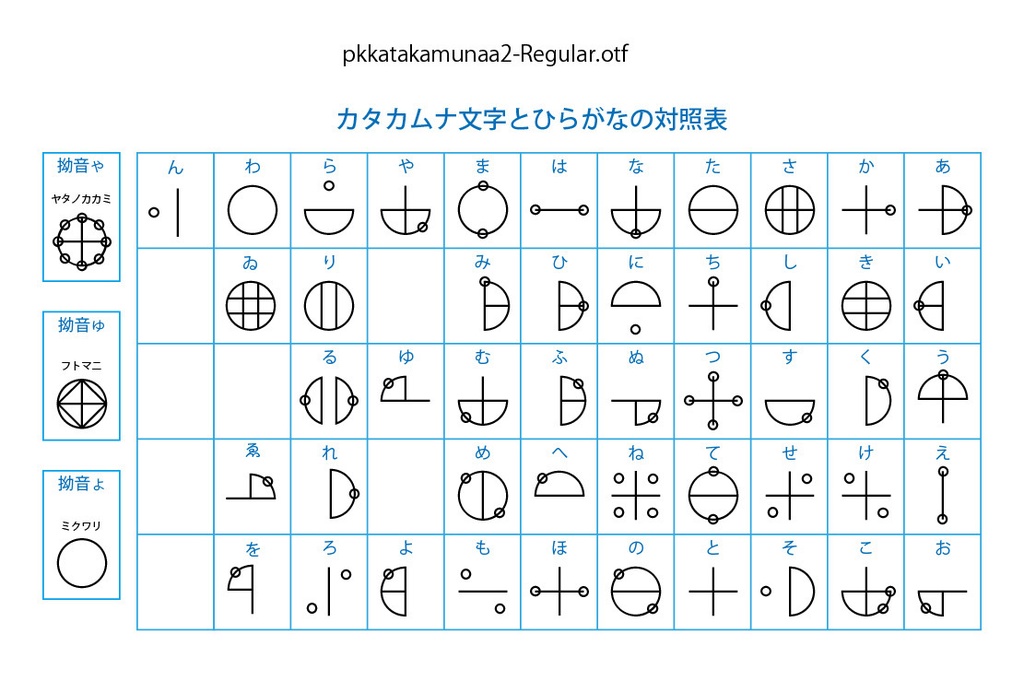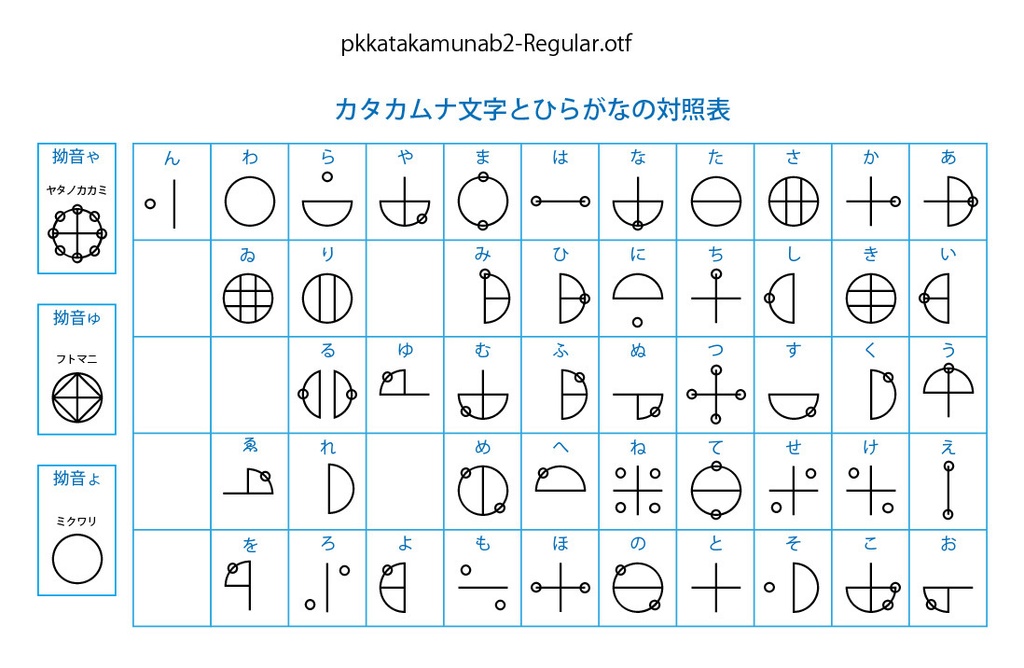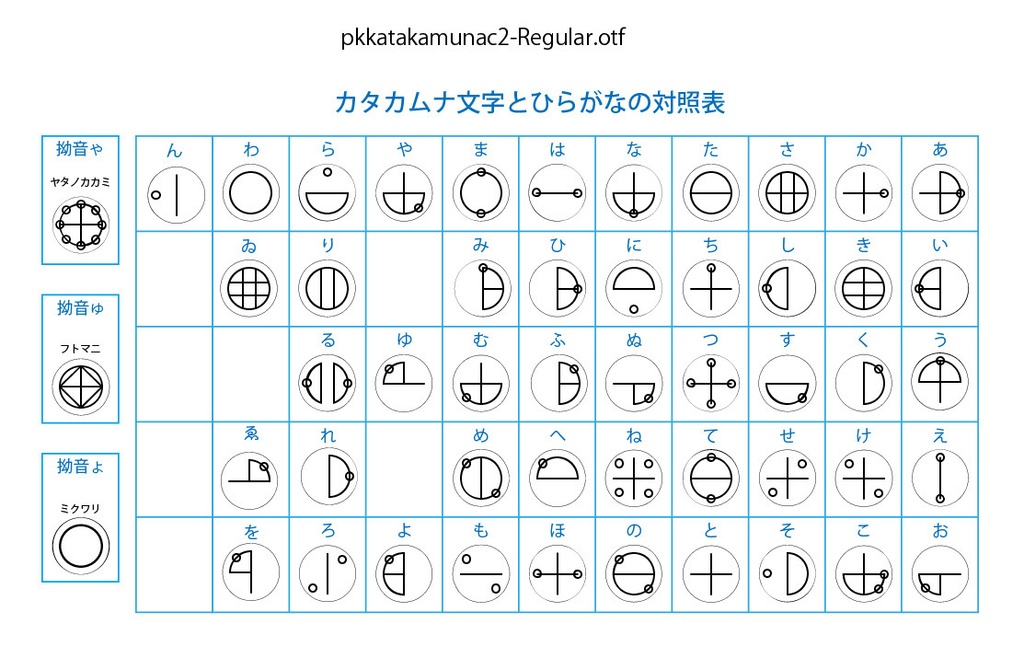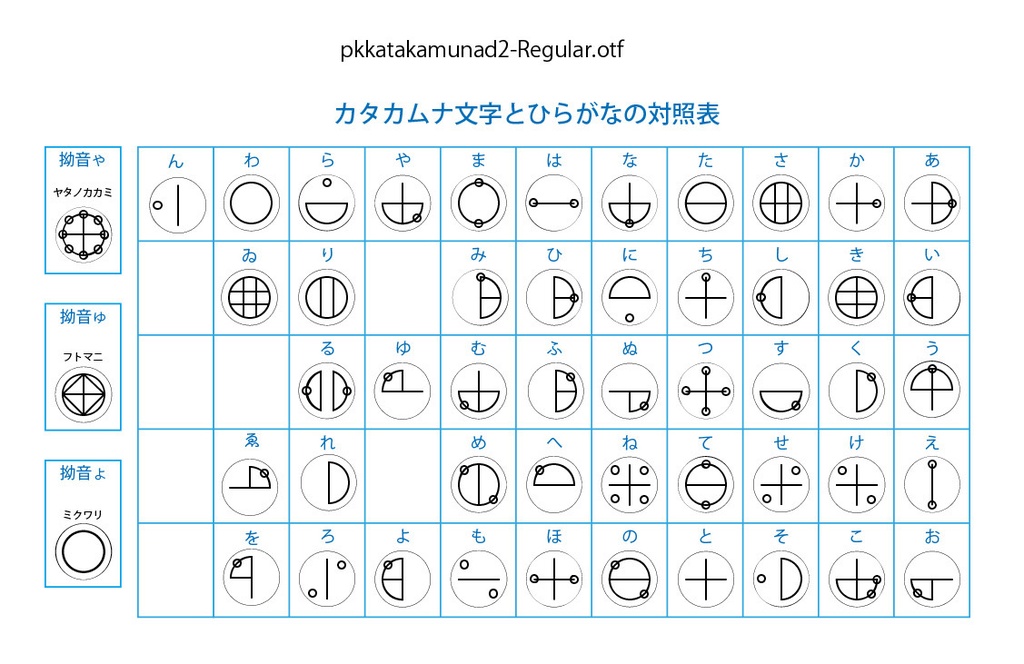
カタカムナ文字のフォントです。 文字を丸囲みしてあるもの、丸囲みしてないものの2種類のフォントを同梱しました。 カタカムナ文字とは、実在不明の「カタカムナ神社」のご神体とされている書物「カタカムナノウタヒ」に使われている、円と直線の組み合わせからなる幾何学的図形の文字です。 1949年楢崎皐月(ならさきこうげつ)によって発見されたものとされており、「カタカムナノウタヒ」にはカタカムナ文字が渦巻状に並んだ、「ウタヒ」(歌)と呼ばれるものが80首書かれています。楢崎の解読によると、カタカムナ文字は日本語のかな48文字に対応するとされています。 ひらがな48文字(ゐゑ含む)を入力すると対応するカタカムナ文字が表示されます。 また、カタカムナノウタヒの中心図象として使われている3つの図象ヤタノカカミ、フトマニ、ミクワリも用意しました。 【収録文字】 ひらがな(あいうえおかきくけこさしすせそたちつてとなにぬねのはひふへほまみむめもやゃゆゅよょらりるれろわゐゑをん) ※ヤタノカカミ、フトマニ、ミクワリをそれぞれ拗音「ゃ」「ゅ」「ょ」に割り当てました。 ※「れ」の表記が資料により2とおりあり、どちらが正しいか判定できないため、右半円に小円がついたものをpkkatakamunaa3-Regular.otf(丸囲みなし)、pkkatakamunac3-Regular.otf(丸囲みあり)とし、右半円のみのものをpkkatakamunab3-Regular.otf(丸囲みなし)、pkkatakamunad3-Regular.otf(丸囲みあり)としてあります。 【データ内容・使用方法】 zipファイルを解凍してください。 OTFファイル pkkatakamunaa3-Regular.otf(丸囲みなし) pkkatakamunab3-Regular.otf(丸囲みなし) pkkatakamunac3-Regular.otf(丸囲みあり) pkkatakamunad3-Regular.otf(丸囲みあり) JPGファイル(カタカムナ文字とひらがなの対照表) comparisona2.jpg comparisonb2.jpg comparisonc2.jpg comparisond2.jpg テキストファイル readme.txt が収録されています。 ご希望のフォントをインストールしてください。 【購入の際の注意点】 商用利用OKです。 使用した場合、ご一報いただけるとうれしいです。Twitterなどで紹介します。 フォントファイルの改変・再配布は禁止です。 ※2024.2.4追記 スペースが■に変換されていたのでファイルを修正しました。